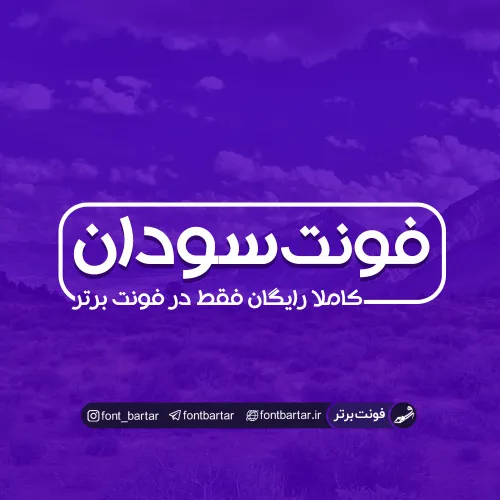
فونت فارسی سودان
فونت سودان مورد استفاده برای:
- طراحان وب سایت و گرافیست های خلاق می توانند از این مجموعه زیبا فونت در طراحی پروژه های تبلیغاتی و تجاری خود کمک بگیرند.